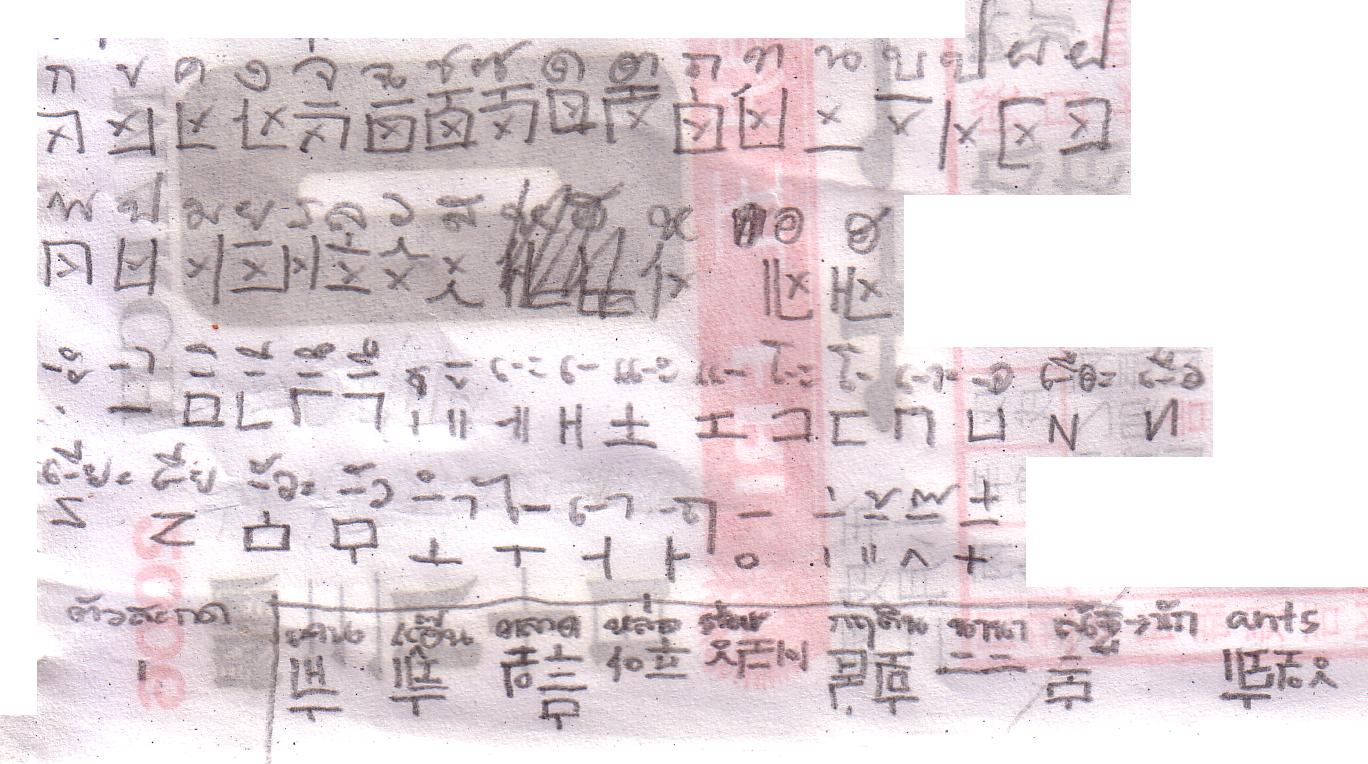
กระจู๋ของคนชอบโชว์ !!!
ทำเล่นๆครับไม่ได้เอาไปใช้ทำอะไร
เลียนแบบต้น
มีกิ่งไม้ด้วย
อักขระที่คิดได้เมื่อกี๊ครับ เท่ชิมิ :26:
เขียนตอนประสมคำแล้วให้ัดูหน่อยดิ  :25:
คำว่า เคน ก็ได้
เขียนไว้ข้างล่างแล้วครับ :11:
:42: ต้องแนบแผนผังการอ่านไปด้วยนะ
เหมือนรหัสลับเลย เยี่ยม  :12:
ถูกมั้ยว่ะ เขียนเดาๆเอา :42:
ยิ่งเขียนยิ่งเกิดบั๊กมากขึ้นเรื่อยๆครับ :36: